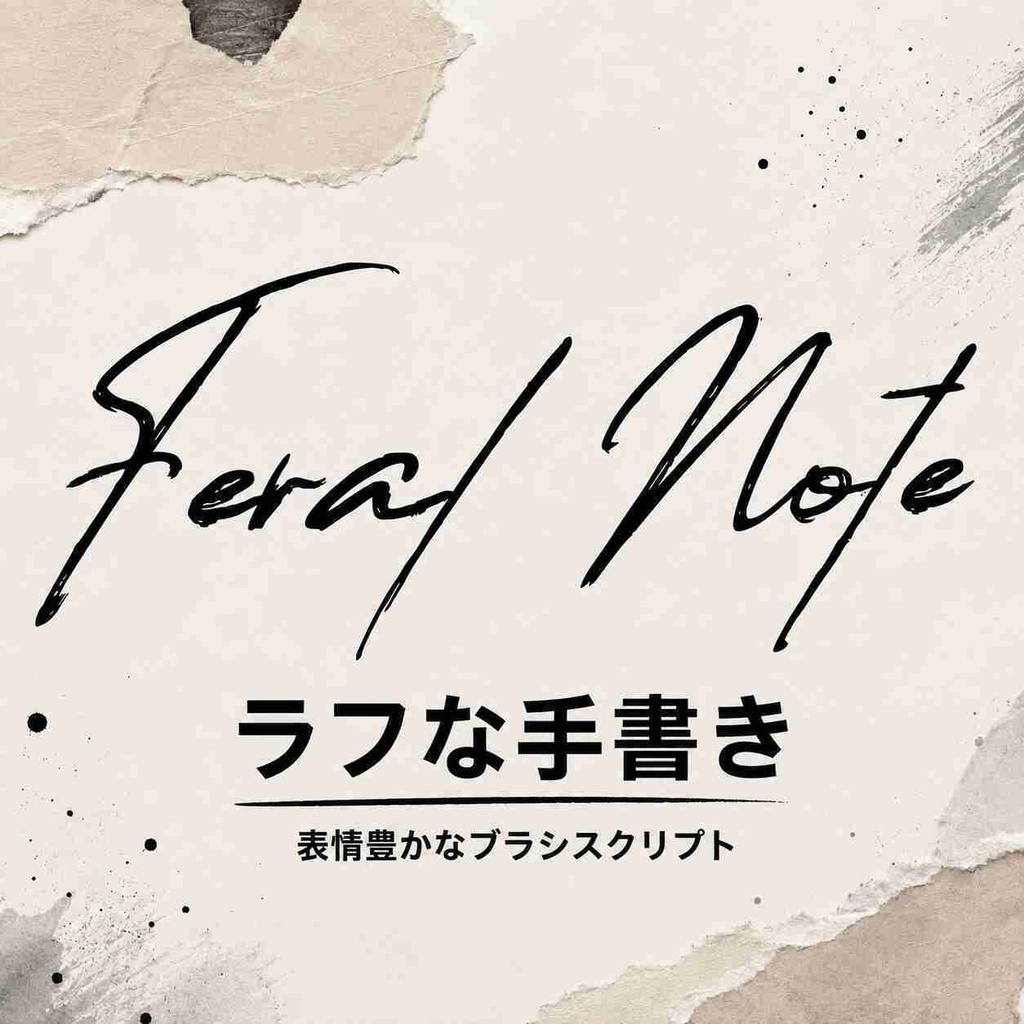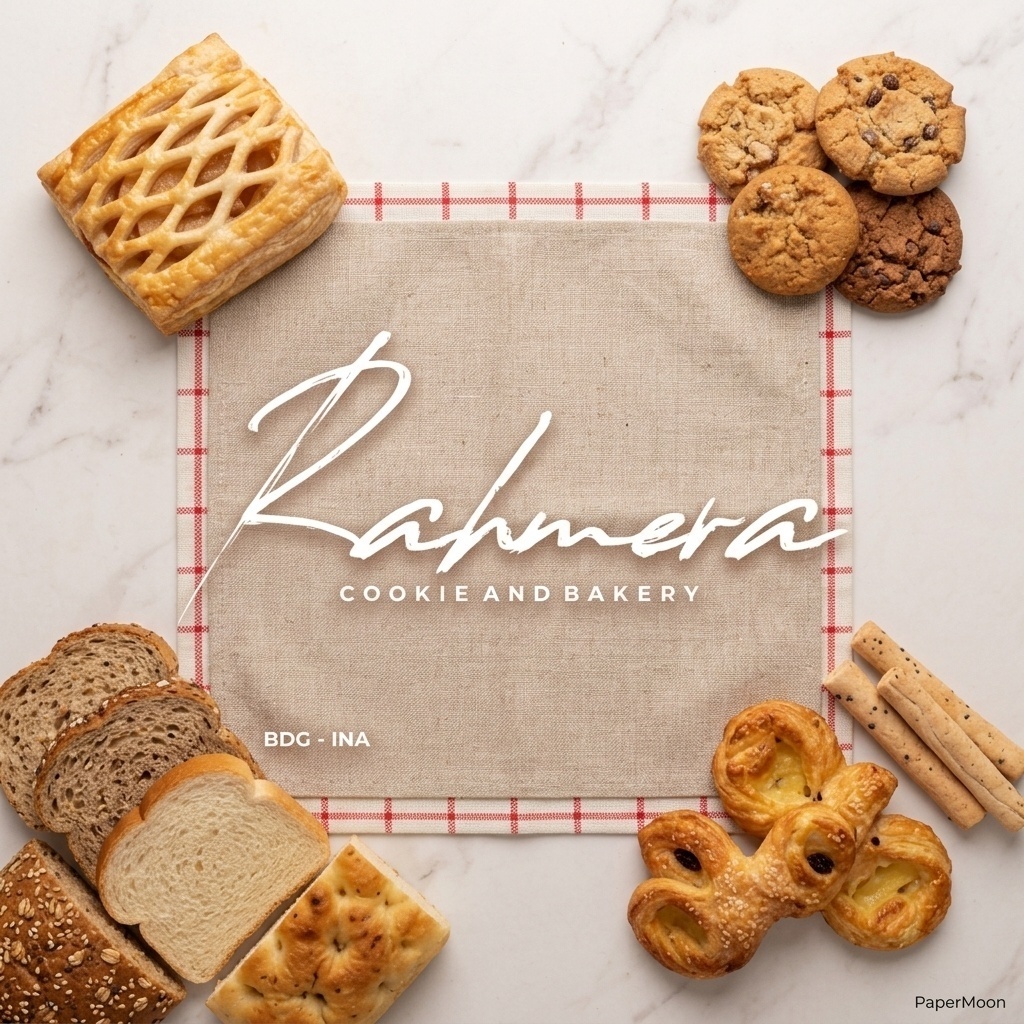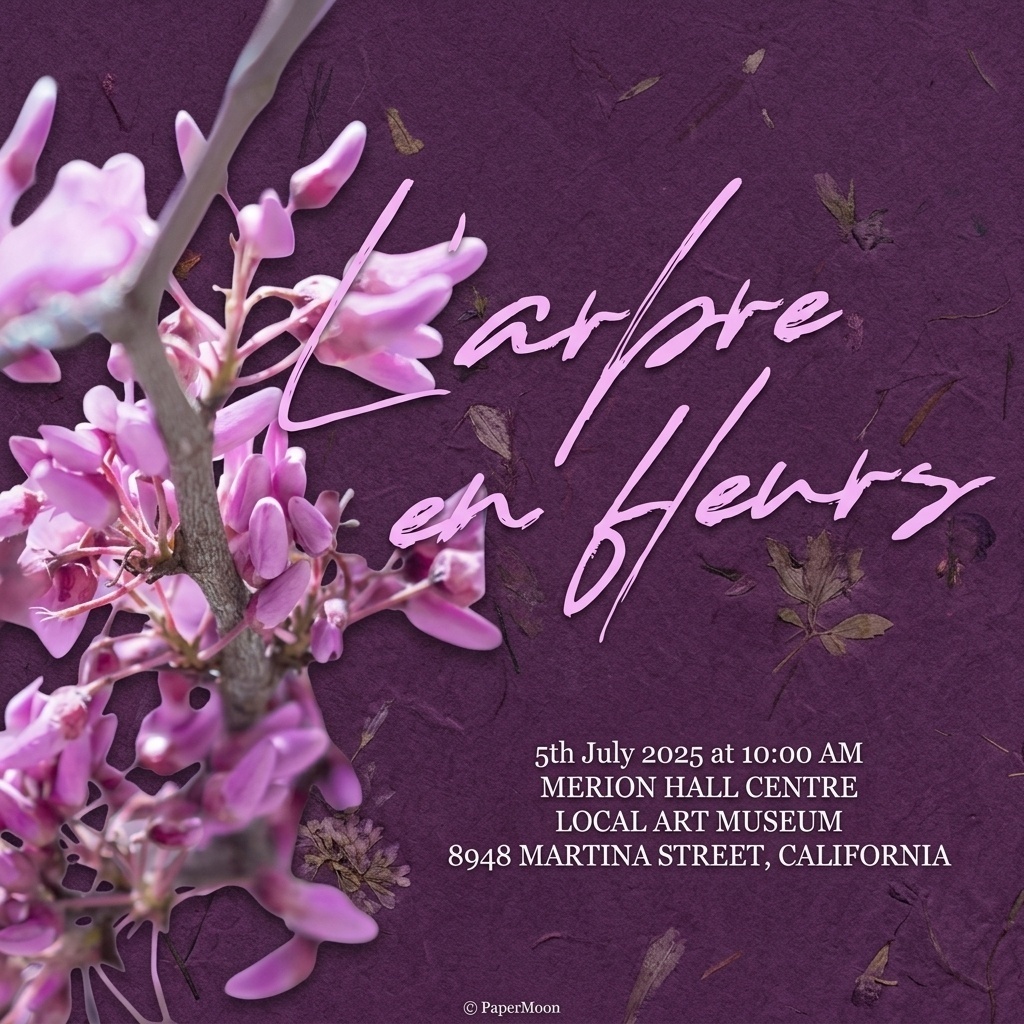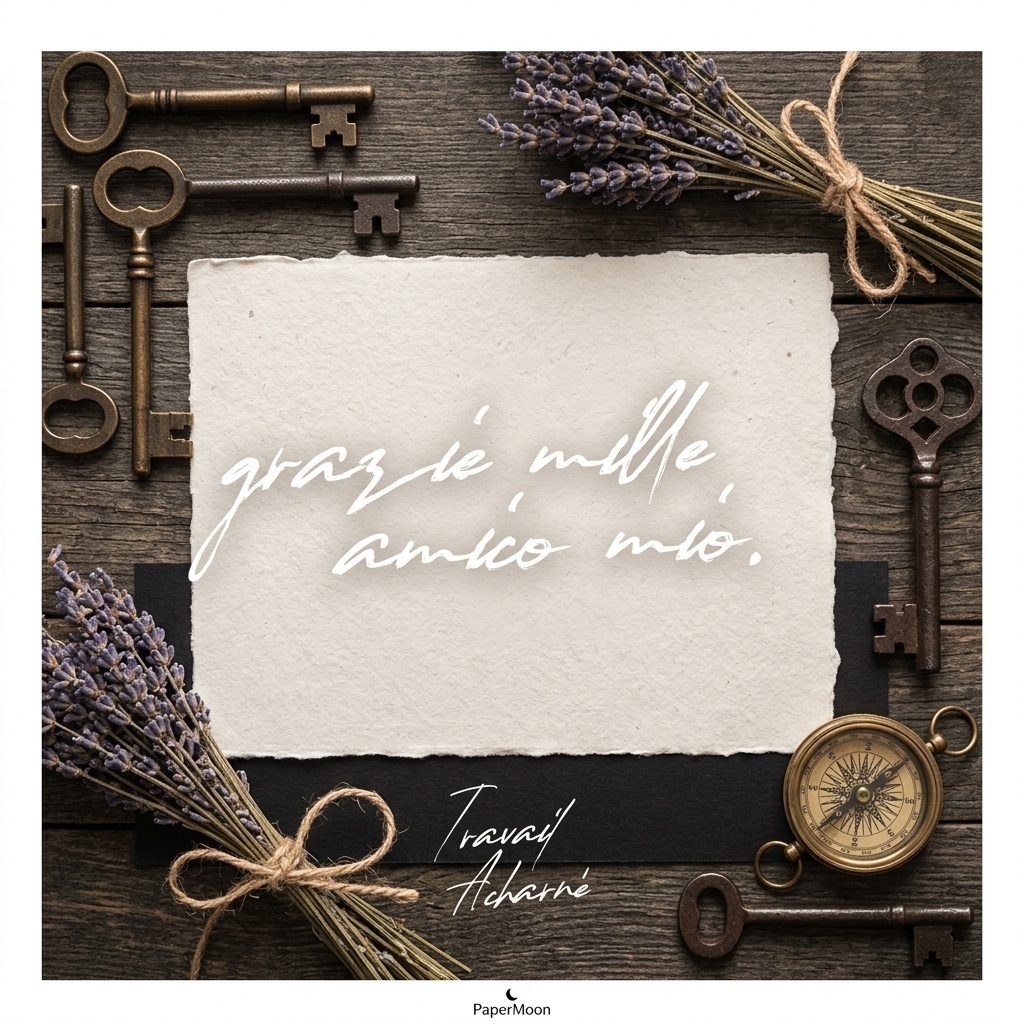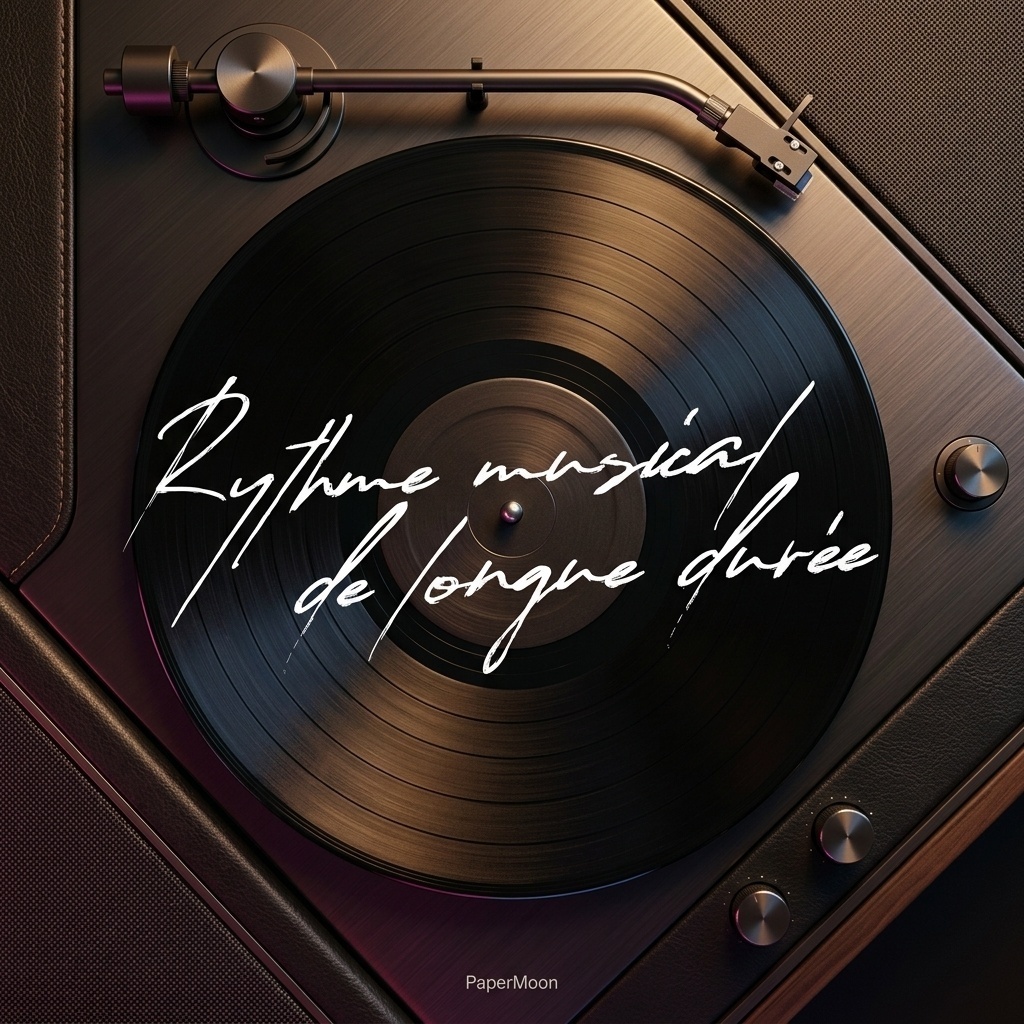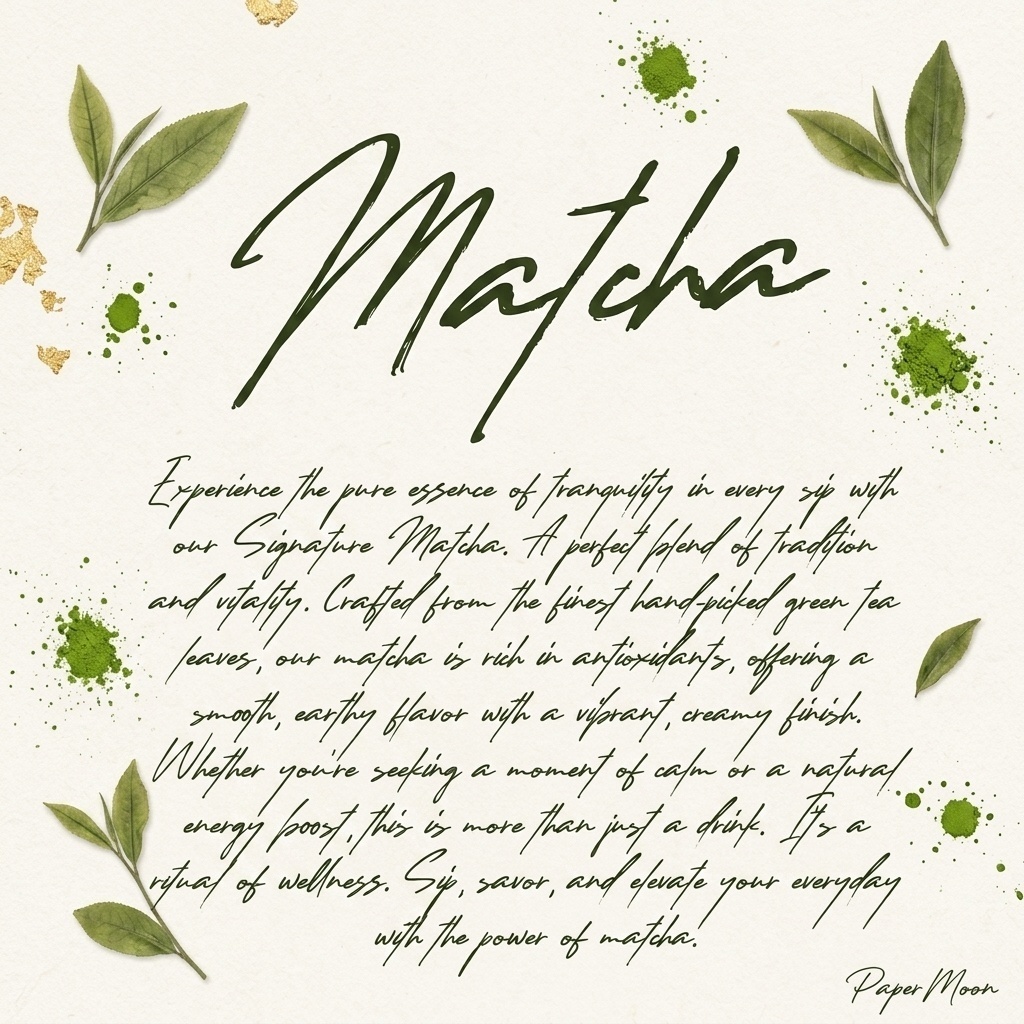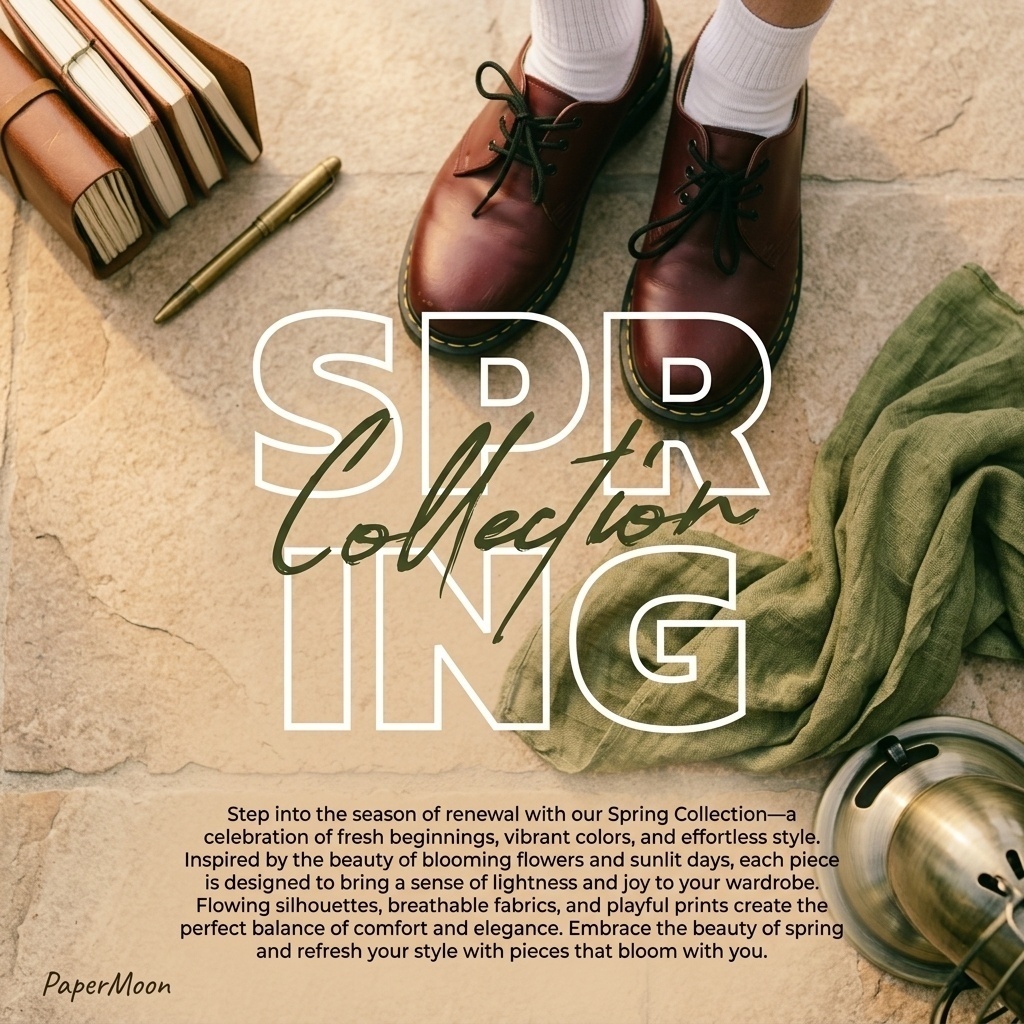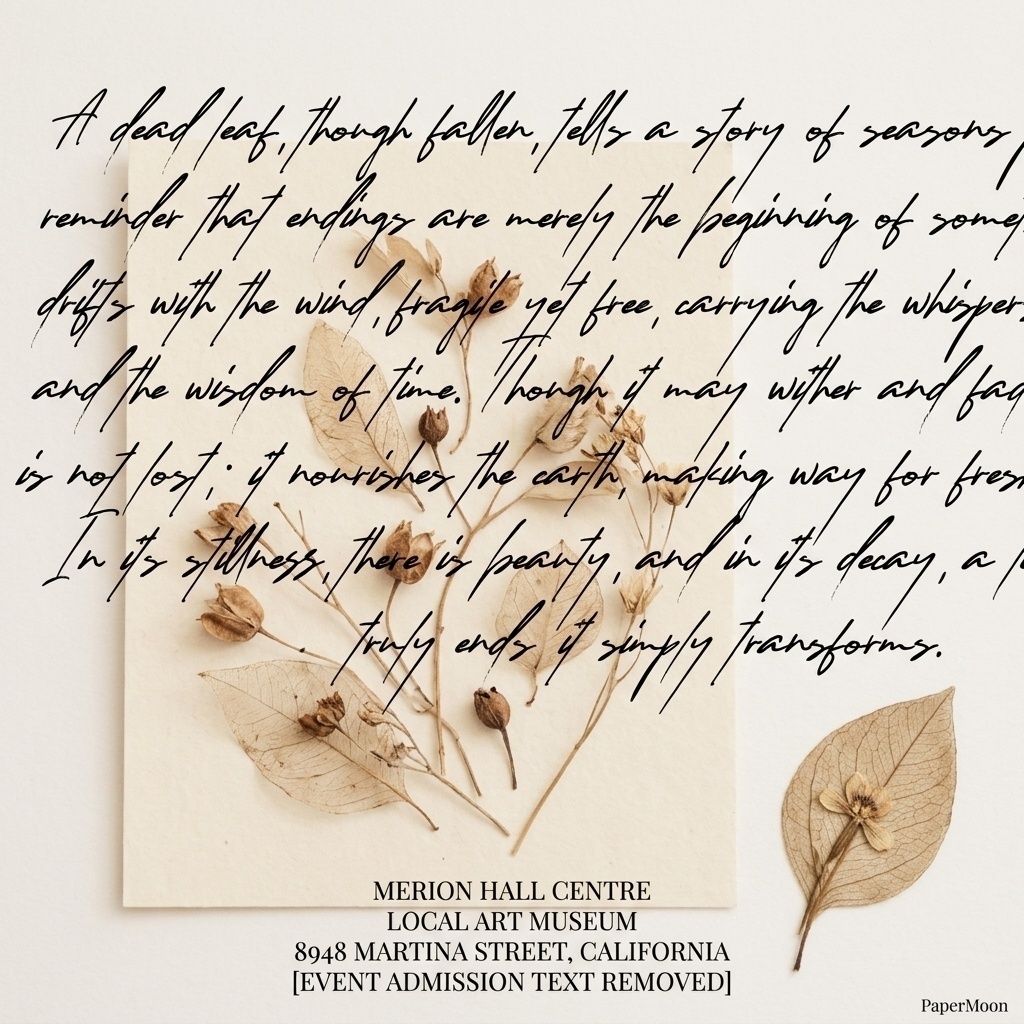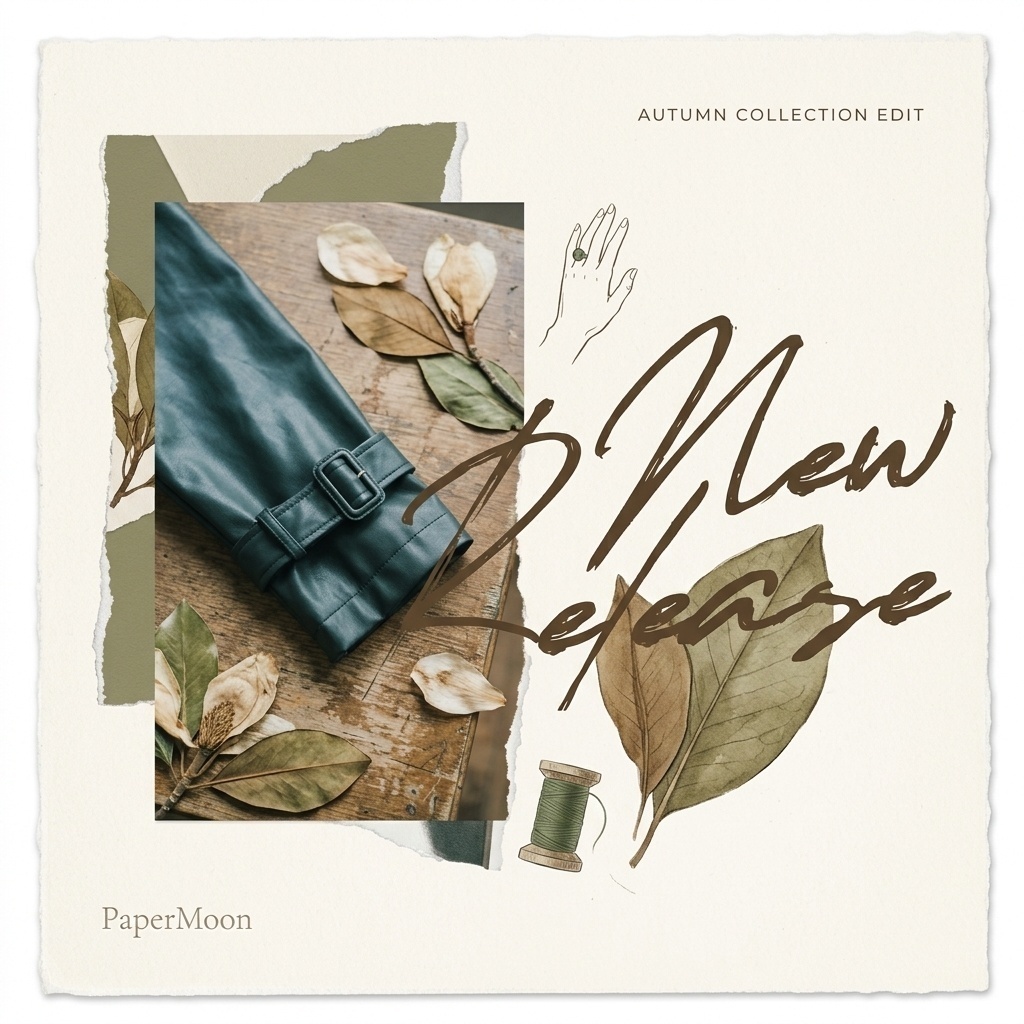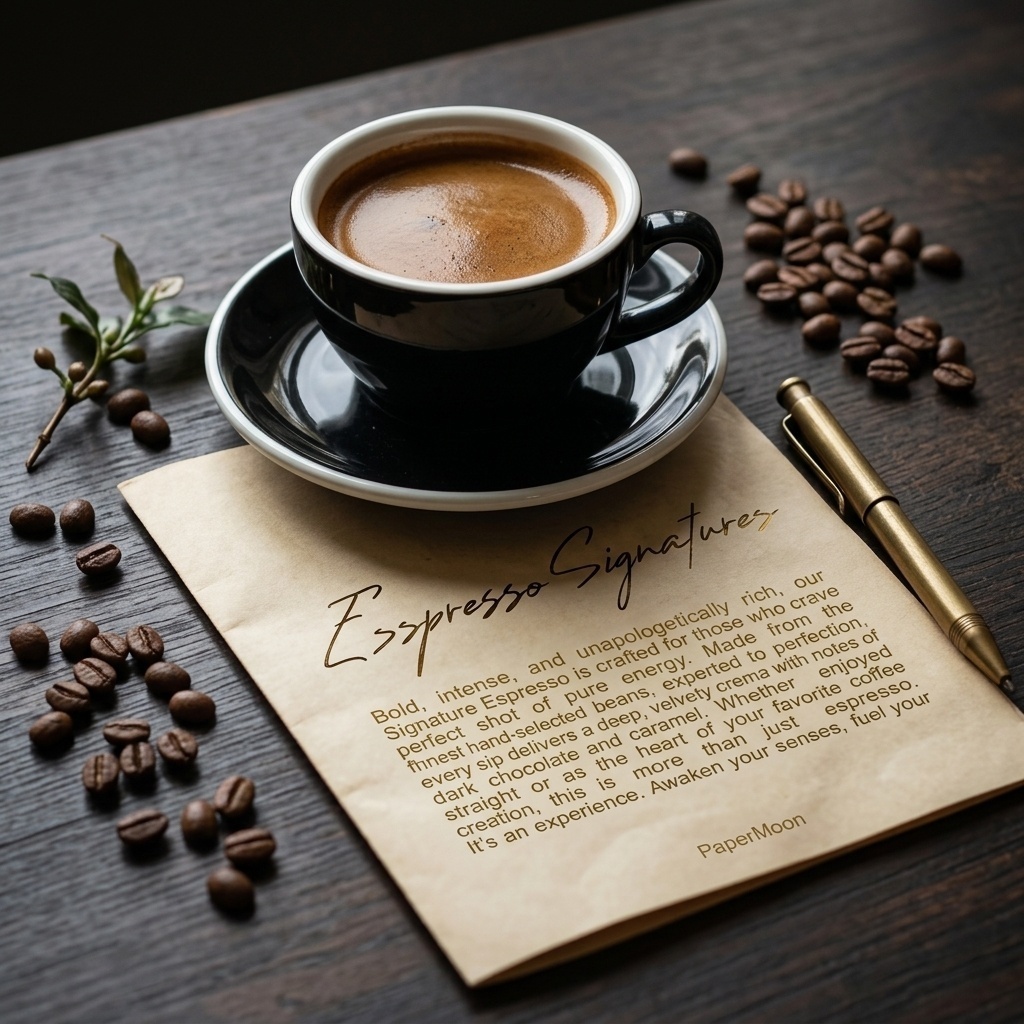
Feral Note | ラフで力強い手書き風英字フォント | ロゴ・ポスター向け
Feral Note(フェラル・ノート)は、荒々しい筆致と手描きの不揃いさを活かした、ラフで表情豊かな英字フォントです。手で描き、スキャンしたような有機的な質感が、ロゴやタイトルにひと目で伝わる強さと、手仕事の温度を加えます。 整いすぎないストロークと大胆な存在感で、ブランドロゴ、ブックカバー、フード・ドリンクのブランディング、広告、映像タイトル、商品パッケージ、引用文、ポスター、フライヤー、文字入り画像などに向いています。デジタル制作と印刷物のどちらにも使いやすい、印象的なディスプレイ向け書体です。 ### 収録内容 - Feral Note フォント - 大文字・小文字 - 数字・句読点・記号 - リガチャ(合字) - 多言語対応 - PUAエンコード対応 ### 用途 - ロゴ・ワードマーク - ブックカバー・装丁 - フード・ドリンクのブランド制作 - 広告・キャンペーン素材 - 映像タイトル・文字入り画像 - 商品パッケージ - ポスター・フライヤー - 引用文やインパクトのある見出し ### 形式 - OTF - TTF - WOFF ### 対応環境 Windows / macOS に対応します。Adobe Illustrator、Adobe Photoshop、Adobe InDesign、Microsoft Wordなど、フォントに対応するアプリケーションで使用できます。インストール方法は通常のフォントと同じです。 ### 利用方法について 商用制作には「商用利用」版、購入者自身の非商用作品・学習・練習・個人制作には「個人利用」版をお選びください。フォントファイルそのものの再配布・再販売を目的とした利用はできません。詳細な許諾条件は、購入前に各バリエーションの案内をご確認ください。